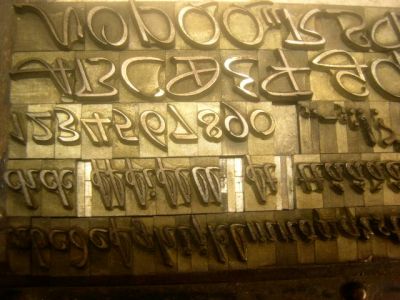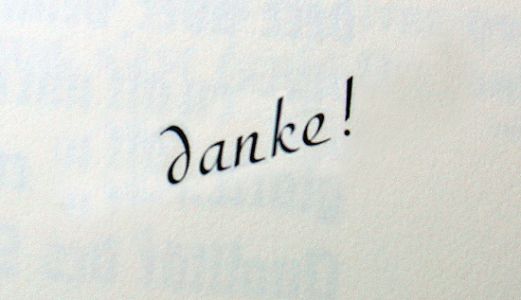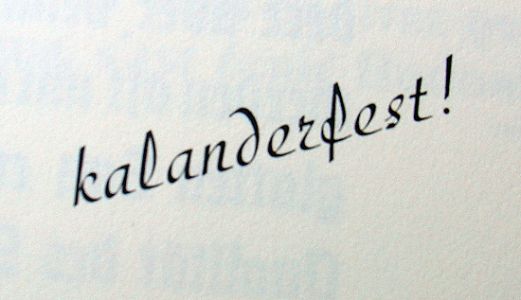
Kalanderfest? Nein, nicht Kalenderfest!
die »Diskus« wirbt mit dem Zusatz »kalanderfest!«.
In der weißen Kunst ist mir das ein Begriff, offene Papiere werden
verdichtet und bekommen eine satinierte Oberfläche.
Die Werbewirksamkeit von »kalanderfest« auf Schrift bezogen, versteh ich nicht ganz?
Auch diese Erklärung »... sie hielten das Prägen der in einer Form geschlossenen Schrift in Matern aus,
von denen dann Stereos gegossen werden konnten und weisen deswegen keinerlei Überhänge auf.«
will mein Hasenhirn nicht ganz verstehen.
Was war besonders an »kalanderfest«?
Sind zum Beispiel folgende Schriften auch kalanderfest: Ariston,
Bauer Bodoni, Caprice, Gladiola, Konzept, New Berolina, Palette?
Hallo Schmorkohl! Hab mal meinen Schwiegervater gefragt, der weiss so was: Kalanderfeste Schriften haben keine Überhänge. D.h. nichts, was über den Kegel vom Bleibuchdtaben hinauskuckt. Nur so konnte man saubere Matern produzieren. Das sieht man an der Schrift ganz schön, finde ich, die Abstände zwischen den Buchstaben. Kannst zwischen allen grade Linien ziehen. Die anderen Schreibschriften haben Überhänge, manvhe ganz extrem. Das weiß bestimmt der Bleisetzer ... Du warst also schon auf dem richtigen Weg.
oben der Satz einer Diskus, unten der einer Lithographia.
Daß man diese Schriften kalandarfest nennt, hatte ich zuvor allerdings noch nie gehört. Es gibt aber eine Schrift, die "Prägefest" heißt:
Die stammt von 1926. Und schon damals sprach trotz des viel weicheren Materials viel dafür, statt der damals üblichen Messingschriften Bleischriften zum Prägen zu verwenden (größere Vielfalt, wesentlich niedrigerer Preis).
Herrlich, diese Vetreterin der "Falzkegelschriften". Im Gegensatz zur "Englischen Schreibschrift", mit ihren überragenden Bleiteilen (die gerne physisch wegbrachen), habe ich die geliebt – obwohl sie mir beim handsetzen immer ungewohnt blieben.